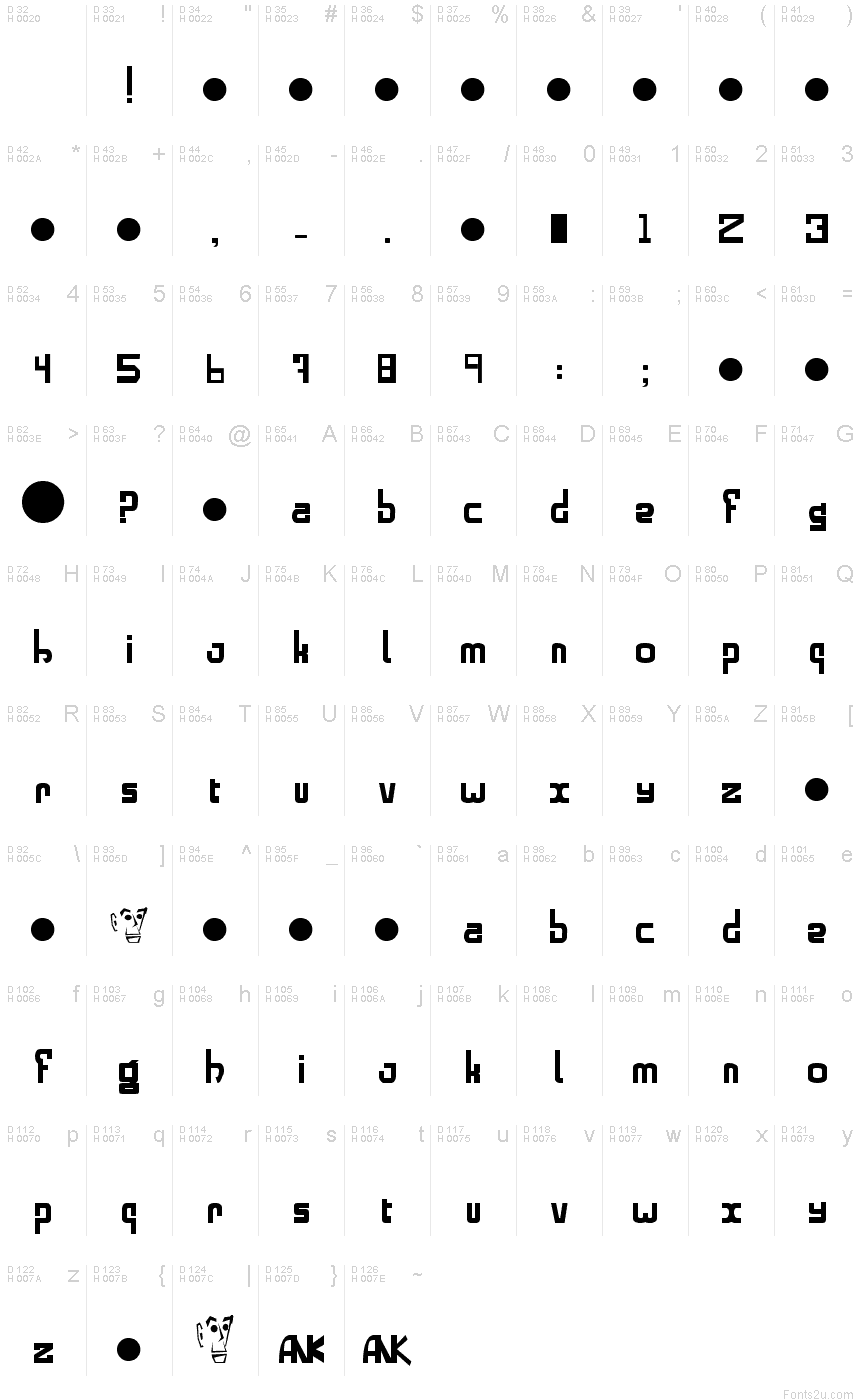
Alphabold è un carattere display futuristico e gratuito che fonde geometrie a blocchi con angoli morbidi e arrotondati, per un look pulito e tech. I tratti robusti e monolineari, uniti alle curve modulari e serrate, danno a ogni parola un aspetto compatto e digitale, come se fosse stata estrusa in plastica lucida partendo dai pixel. Le lettere si posizionano vicine e con decisione, creando un ritmo forte che si legge velocemente anche al primo sguardo.
Con Alphabold, i titoli sembrano comandi di una console o schermate di un film di fantascienza; questo font gratuito è quindi perfetto per loghi di videogiochi, branding e-sport, poster di eventi tech, grafiche cyberpunk, schermate di avvio di app e thumbnail accattivanti per YouTube. Esprime al meglio il suo potenziale nelle grandi dimensioni, dove le forme massicce e gli angoli retti si incastrano alla perfezione. Per il testo secondario, abbinalo a un semplice sans serif geometrico con un peso più leggero, così da mantenere il layout equilibrato e leggibile.